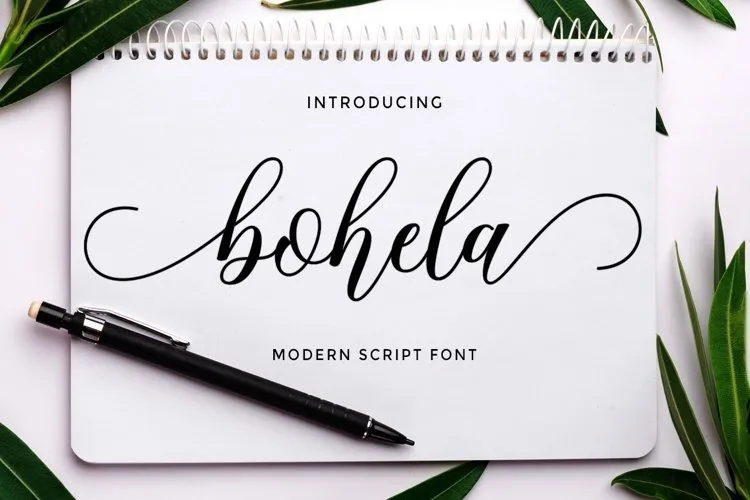
Esta fonte é perfeitamente descrita como um script elegante chamado Bohela Font, criada no prestigiado marketplace 99designs para designers apaixonados por letras fluidas e amorosas. Descrito com uma nota de elegância, esta fonte traz a beleza da escrita em cada traço. Ideal para diversos projetos personalizados, desde logotipos e embalagens de produtos até convites de casamento, rótulos ou capas de livros, Bohela é perfeita para headlines, marcos de viés, assinaturas e muito mais. Seja onde você olhe, a elegância desta fonte vai destacar seu trabalho com um toque suave e refinado, tornando cada projeto especial.